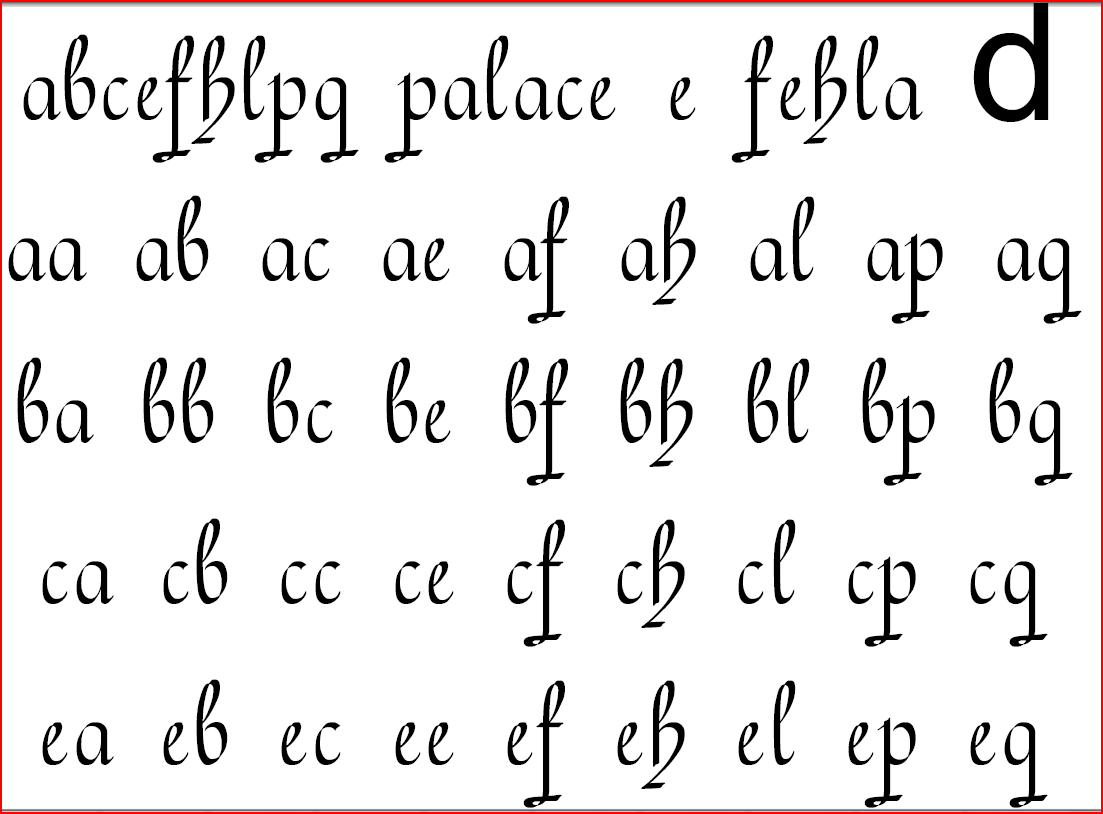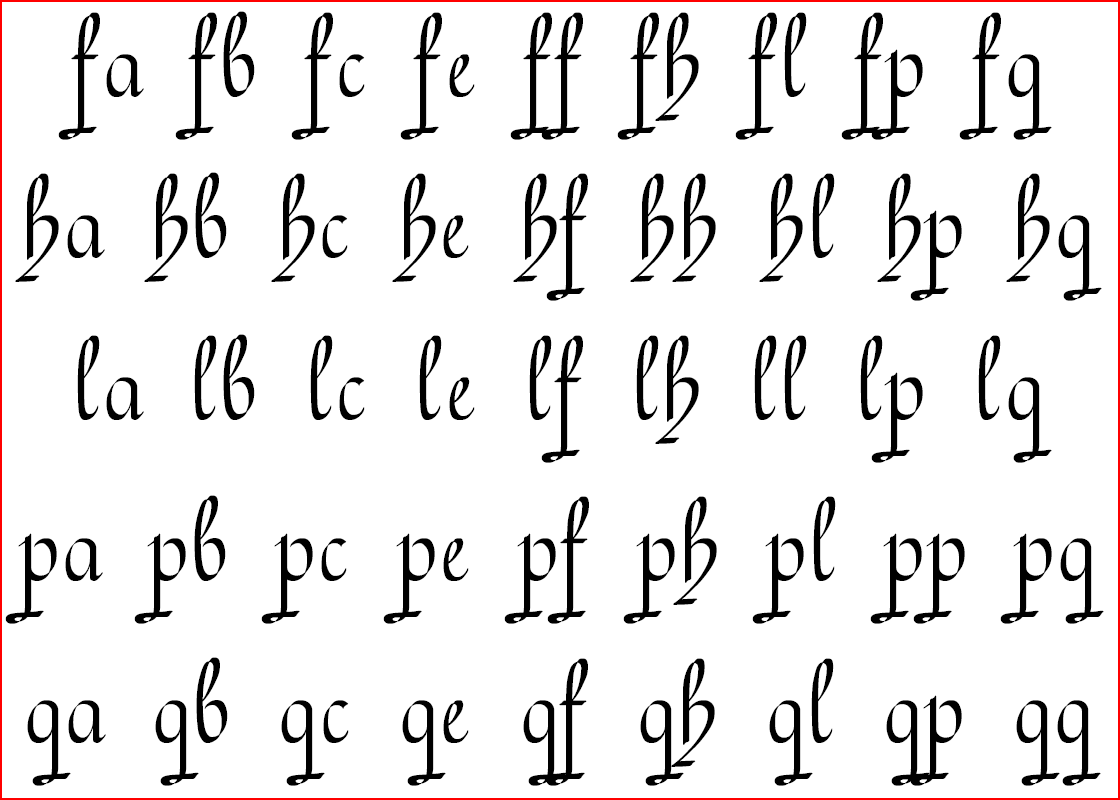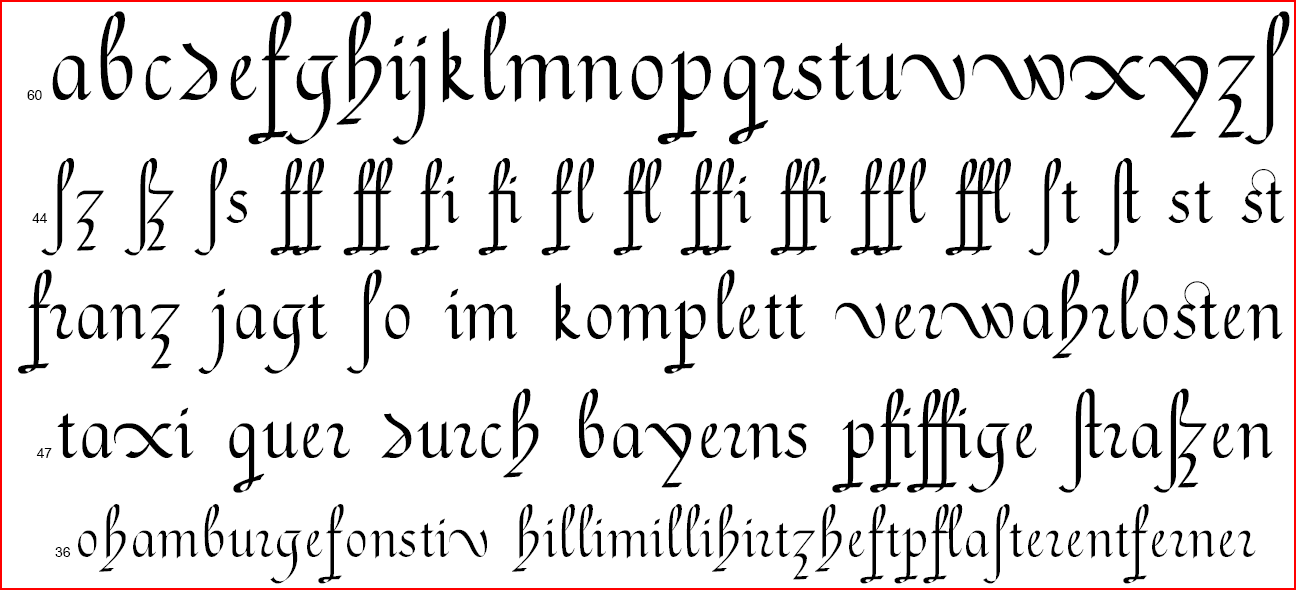
Letra Redonda von Juan Claudio Aznar de Polanco schon verwendet?
Ich hatte kürzlich eine Buchbestellung bei Jokers mit Tschicholds "Meisterbuch der Schrift" "arrondiert" ;-) und blätter mich da gerade durch ...
Dabei bin ich über die Seiten 148/149 gestolpert.
Letra Redonda (Spanische Rundschrift) aus dem Buche "Arte nueva de escribier" des Juan Claudio Aznar de Polanco, Madrid 1719. Kupferstiche, hier leicht verkleinert. Gewiß keine unmittelbare Vorlage; doch könnte ein wirklicher Meister aus den Buchstaben n, o, p, l, e, i und bei sehr vorsichtigem Gebrauch der Formenwelt der zum Teil für uns ja kaum lesbaren Versalien ein modernes Alphabet entwickeln. Die Gemeinen sind von großer, besonderer Schönheit.
Tante Gugel und erste Suchen in Schriftenverzeichnissen brachten die letzten Tage keine Treffer, die vermuten lassen, dass sich schon ein "wirklicher Meister" fand, der diesen Ruf erhörte.
Ist dem so? Oder hat sich schon wer an einem Nachbau versucht?
Da das Meisterbuch hier vermutlich bekannt ist, tippe ich mal drauf, dass es hier irgendwem bekannt wäre, gäbe es schon einen Nachbau?
Ansonsten wäre es evtl. eine reizvolle Aufgabe, sowas mal mit fontforge zu basteln zu versuchen... ;-)
Soderle, habe die Rodonde von Polanco mal gescannt, auch um sie bei WTF suchen zu lassen.
Das blieb ohne Ergebnis im Sinne der Frage der ersten Nachricht, dass es sie schon digital gäbe (jedenfalls dort, gibt's noch andere ähnliche Suchen?)
Laut spanischem Originalbuch, dass es bei books.google in mindestens eins / zwei Versionen gibt (Kaiptel Redonda beginnt jeweils eine Seite weiter), sagt, wenn ich das richtig verstehe *) und zuordne **), dass es folgende Buchstaben sein sollen:
a b c d e f l g h (y laut Text?!? ***)) (i, wird nicht beschrieben im Text) m n o p q r s t u (anderes p????) v x y z
A B(+R+P daraus variiert) C D E F G H (I? laut Text L?) M N O Q (R-Variante) (noch eine R-Variante??) S T V-Corazon (V-Variante) X (L-Variante?) (J?) (F-Variante?)
*) ich nix spanisch ... Übersetzungsversuch mit translate-google unter Berücksichtigung von ſ, x->j, z->c, ſs->s und anderer Rechtschreibungsanpassungsvermutungen, sowie LEO und dem Versuch logischen Überlegens ...
**) Offenbar scheint der Text die Reihenfolge in den Originalgraphiken zu verwenden, Ausnahme: nur im Text beschrieben ist das "andere s" als Variante des f, also wohl das ſ.
***) könnte ein j gemeint sein?
Das kleine d sollte man wohl mit Oberlänge gestalten in der älteren "griechisch anmutenden" Variante. Das große D ist halbwegs erkennbar?
Ist das T als solches erkennbar?
Das G wohl eher nicht lesbar?
J auch schwierig erkennbar ... Könnte auch ein Z sein ;-)
Das y sollte man wohl stutzen ...
Ebenso könnte man dem M locker einen Kringel moppsen ...
w und k fehlen ...
Ebenso K, U, W und je nach Interpretation der offenen Fragen noch paar mehr bzw. neu zu designen ...
Soderle, die ersten Buchstaben sind in fontforge als erster schneller Versuch reingemalt ...
Aznar de Polanco scheint den Font zwar als mathematisch gestaltet zu betrachten, aber mit dem Scans im Hintergrund sieht man dann doch kleiner Abweichungen zwischen eigentlich ähnlichen Elementen. Einige werde ich wohl mitmachen, andere vereinheitlichen, schaun mer mal ...
Die nächsten Tage werden evtl. nicht so produktiv, daher mal erste Zwischenergebnisse, Kommentare sehr willkommen ... ;-)
Ich erlaube mir mal einen kleinen Kommentar:
Als Fingerübung ist das sicher nicht schlecht, aber Tschicholds Begeisterung kann ich ehrlich gesagt nicht nachvollziehen. Ich finde, diese Schrift sieht aus, als hätte da ein Kalligraph beim Fernsprechen ein bißchen vor sich hin gekritzelt.
Damit will ich Dir nicht die Freude an Deiner Arbeit nehmen, Geschmäcker sind bekanntlich sehr verschieden! Wenn die Schrift für normale Anwendungen einmal benutzbar werden soll, mußt Du aber einige Buchstaben deutlich überarbeiten, damit man sie überhaupt erkennen kann.
ich empfinde die schrift als unausgewogen. einige glyphen stehen statisch wie säulen rum, andere sind von einer beschwingtheit, die ich eher bei zierkursiven suchen würde. der federduktus einiger glyphen ist zwar sehr ansprechend, doch insgesamt könnten die glyphen verschiedenen schriften entstammen.
Im Zitat, welches Mueck eingangs zitiert, steht ja auch schon eine Einschränkung, die Tchichold selber in Bezug auf diese Schrift macht:
… Gewiß keine unmittelbare Vorlage; doch könnte ein wirklicher Meister aus den Buchstaben n, o, p, l, e, i und bei sehr vorsichtigem Gebrauch der Formenwelt der zum Teil für uns ja kaum lesbaren Versalien ein modernes Alphabet entwickeln. …
Betrachte ich die erwähnten Buchstaben, dann interpretiere ich das so, dass auch Tschichold die sehr schwunghaften Buchstaben als zu speziell empfunden hat und er als formalen Ausgangspunkt für eine Neuinterpretation der Schrift eher die von ihm genannten, in ihrer Form gemäßigten Buchstaben empfehlen würde.